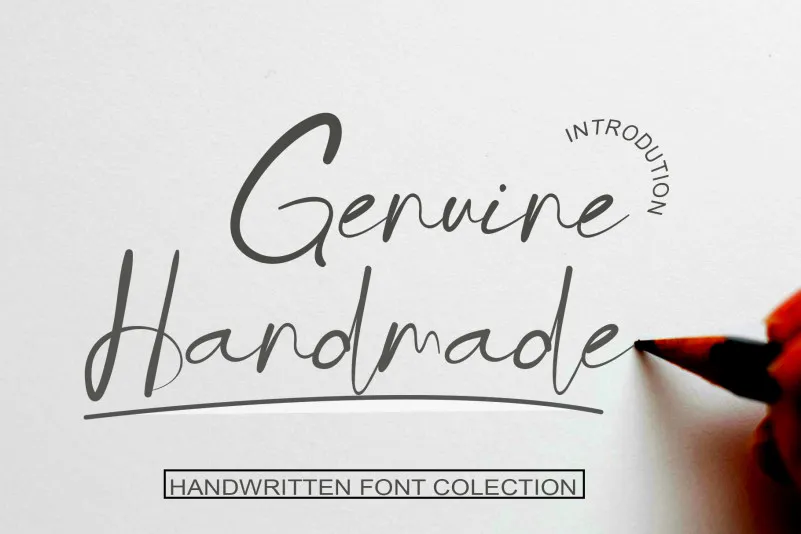
Genuine Handmade Font
A Genuine Handmade Font é uma elegante tipografia script inspirada na calligrafia clássica, que oferece um ar contemporâneo ao mesmo tempo em que manter a beleza inatacável e perfeita. Este tipo de fonte não é muito grossa nem fina, mas mantém um equilíbrio e variedade que fazem da Genuine Handmade uma escolha ótima para destacar o seu projeto. Inspirada no estilo das antigas chamigrafias, esta fonte é projetada para ajudar a melhorar o aspecto do seu trabalho, tornando-a perfeita para nomes de empresas, cartazes, editoriais e qualquer outro aplicativo que você precise para dar um toque pessoal em sua publicação. Como uma fonte escrita à mão genuína, ela traz vida e alma às suas criações digitais, destacando a criatividade e o cuidado com detalhes que só as obras de arte manuscritas podem oferecer.